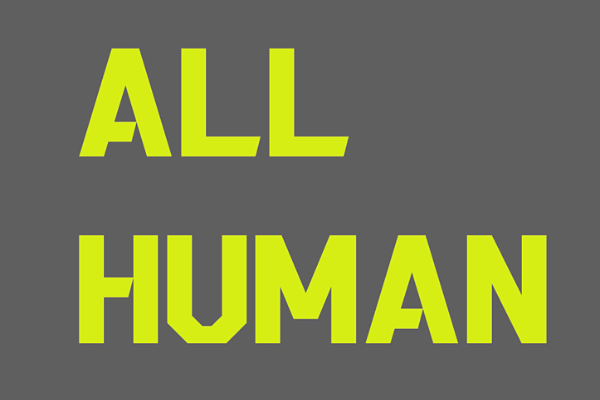
ZQKfreefont
ZQKfreefont是庆科字体匠心打造的英文(拉丁)Display字体,以现代粗体风格为设计注入硬朗力量。作为一款专为视觉焦点而生的字体,ZQKfreefont字形方正如切割后的砖石,重心居中稳若磐石,中宫适中的结构让字符排布疏密有度,视觉平衡感十足。 ZQKfreefont的笔型设计暗藏巧思:全字以利落直角为骨架,方头笔画如刀削般干脆,摒弃圆润弧度,每一笔都带着工业风的利落;而笔画间巧妙断开的处理,则打破传统连笔的沉闷,在硬朗基调中注入呼吸感,让字符节奏分明不呆板。字重饱满的粗体设定配合均匀一致的笔画粗细,更让线条在放大后依旧清晰锐利,细节处不见拖沓,尽显力量美学。 作为免费商用字体,ZQKfreefont适配常规英文(拉丁)字符集,无论是标题设计、品牌LOGO创作,还是海报、包装中的视觉焦点打造,都能以鲜明个性助力设计高效落地。若你需要一款自带“硬核气场”的现代粗体英文Display字体,ZQKfreefont定能成为设计中的点睛之笔。